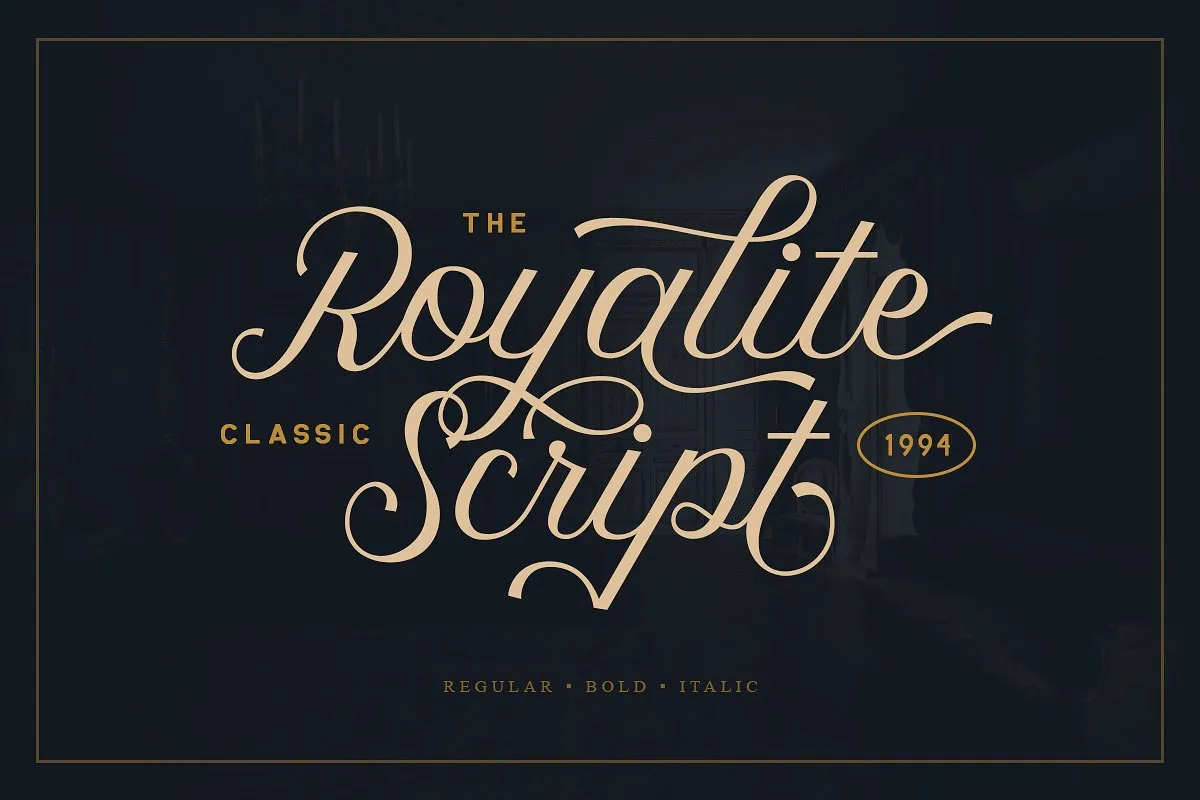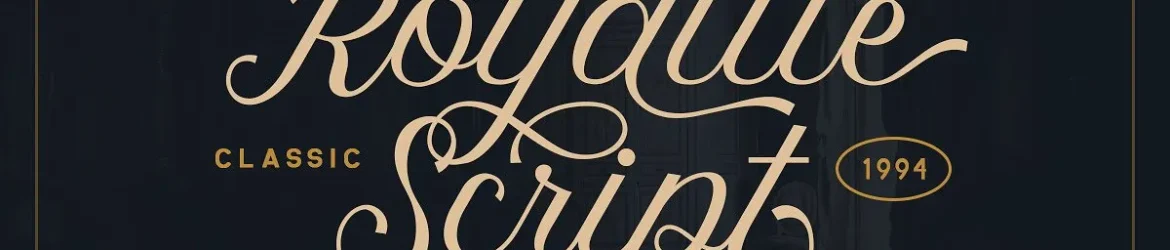
Royalite Script Font – Download Grátis
Royalite Font é uma elegante tipografia script moderna que oferece um toque sofisticado ao seu design. Ideal para personalizar assinaturas ou criar logotipos únicos, esta fonte inclui alternativas estilizadas e swashes para fazer o texto se destacar ainda mais. Para aqueles que buscam uma tipografia clássica moderna, Royalite é a escolha certa. Com sua elegância singular, esta font permite criar cartões de aniversário encantadores, criações de moodboard sofisticadas e qualquer outra coisa sonhada em um estilo delicado e luxuoso. Tempere seus projetos com uma pitada de Royalite Font para adicioná-los ao seu coquetel único de design.